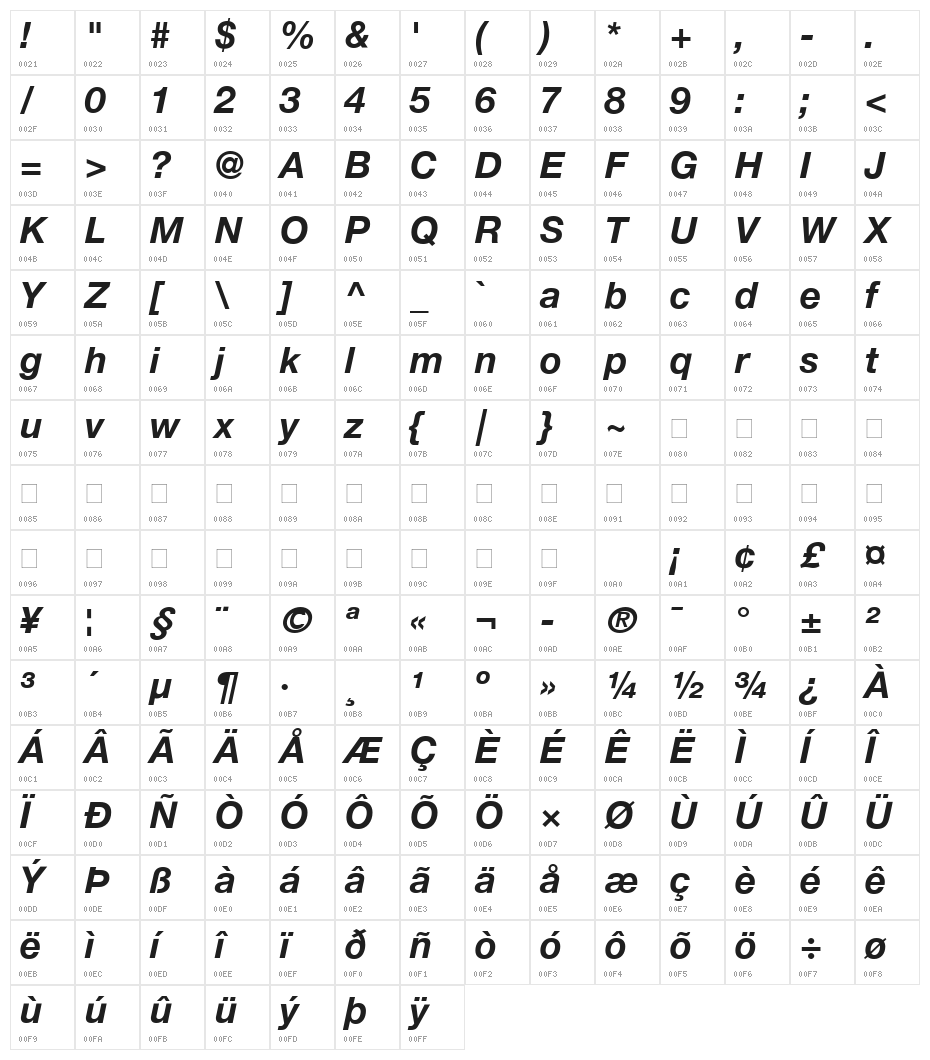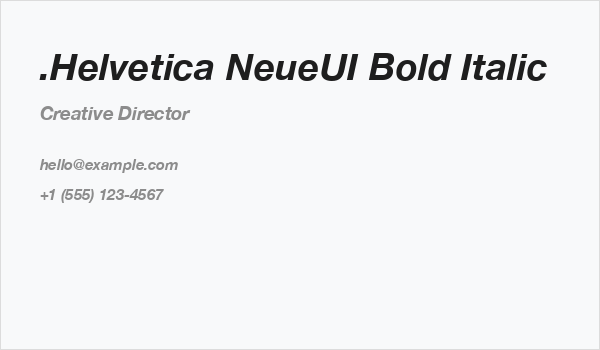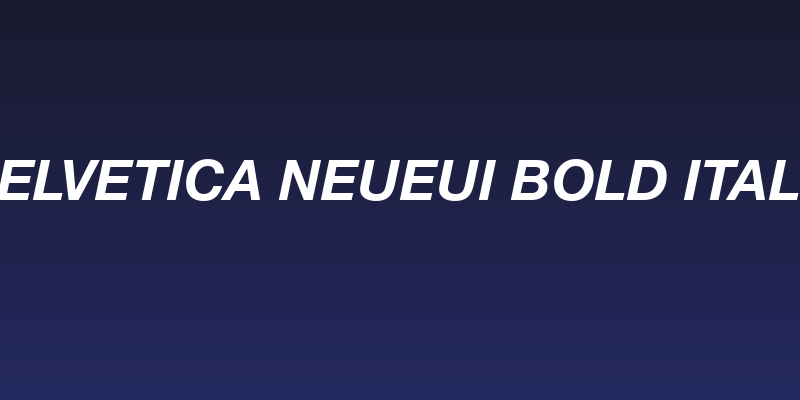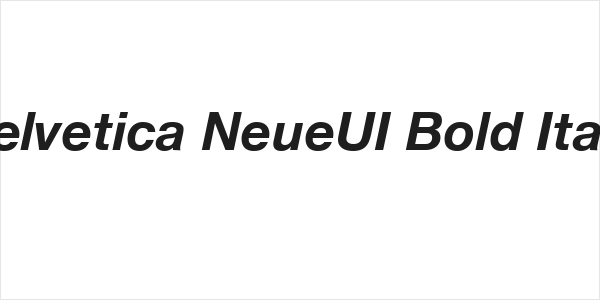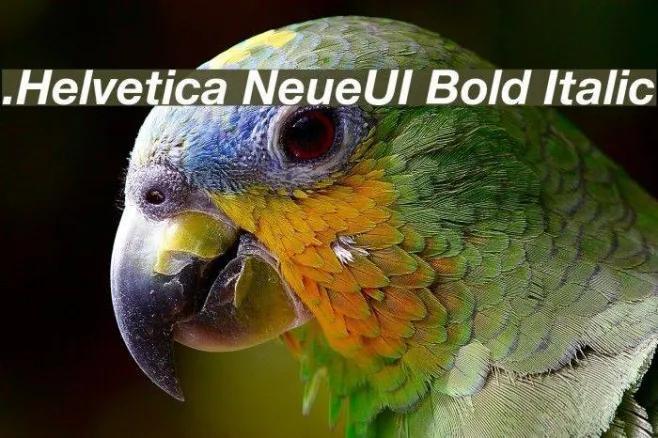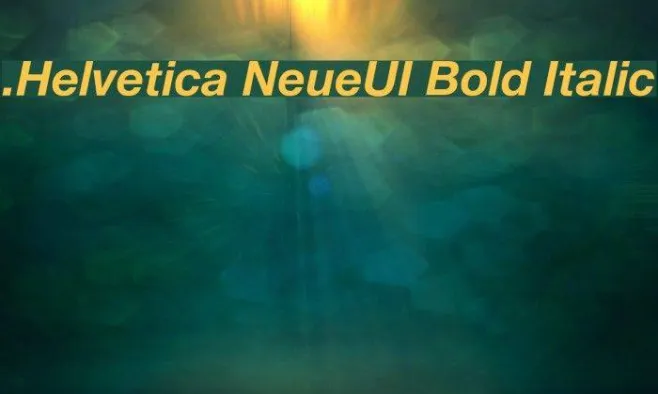
.Helvetica NeueUI Bold Italic Font
| Nom | .Helvetica NeueUI Bold Italic |
| Poids | Bold Italic |
| Cas d'utilisation | Headlines, Logos, Digital Interfaces |
| Projets proposés | Ideal for branding, advertising, headlines, and digital interfaces where a strong, modern presence is required. |